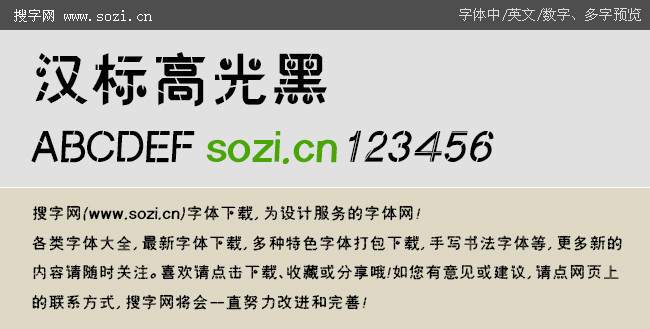
漢標高光黑
搜字網(wǎng)給大家提供一款漢標高光黑中文字體下載,漢標高光黑根據(jù)黑體的字形創(chuàng)作而來,字體筆畫中添加了大量的斷筆,產(chǎn)生高光照射的光線效果。適用于大標題、包裝設(shè)計、海報設(shè)計等應(yīng)用。(本字體為個人非商用版,如需要商用請聯(lián)系官方購買版權(quán))